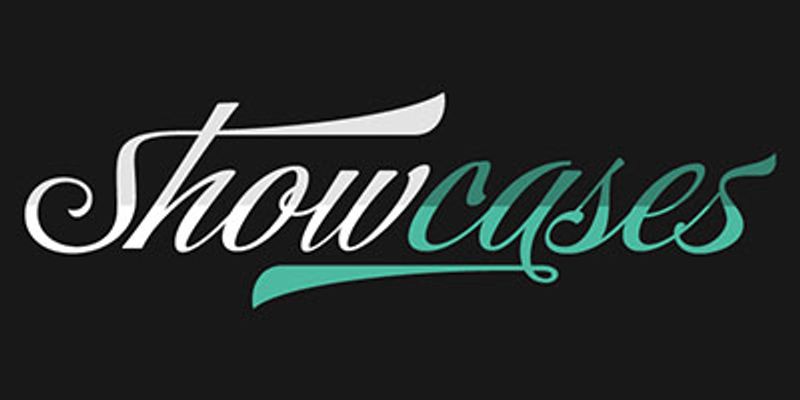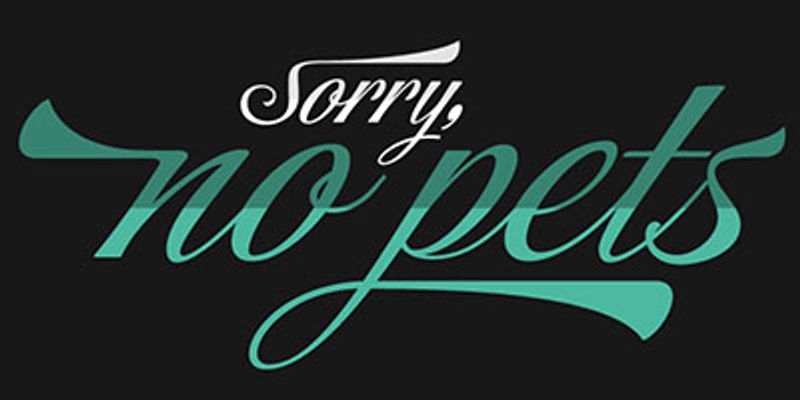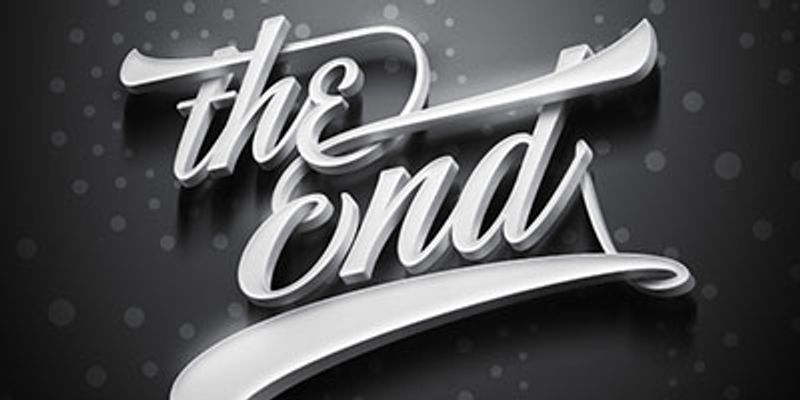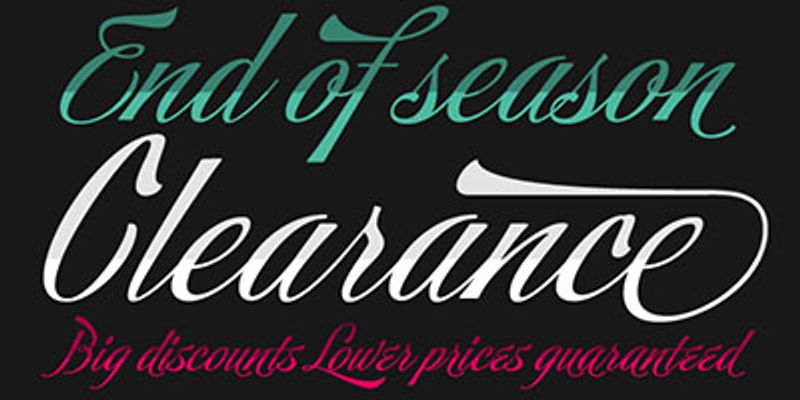
Storefront es lo que los prolíficos y talentosos pintores de letreros estadounidenses de las décadas de 1920 y 1930 habrían creado si hubieran tenido acceso a las tecnologías avanzadas de letras y tipos que tenemos hoy en día. Enraizado en una muestra incompleta del alfabeto Alf Becker, Storefront es mi sobredosis habitual de alternativas y florituras, mi eterno intento de dar a la composición tipográfica esa impresión hecha a mano siempre esquiva.